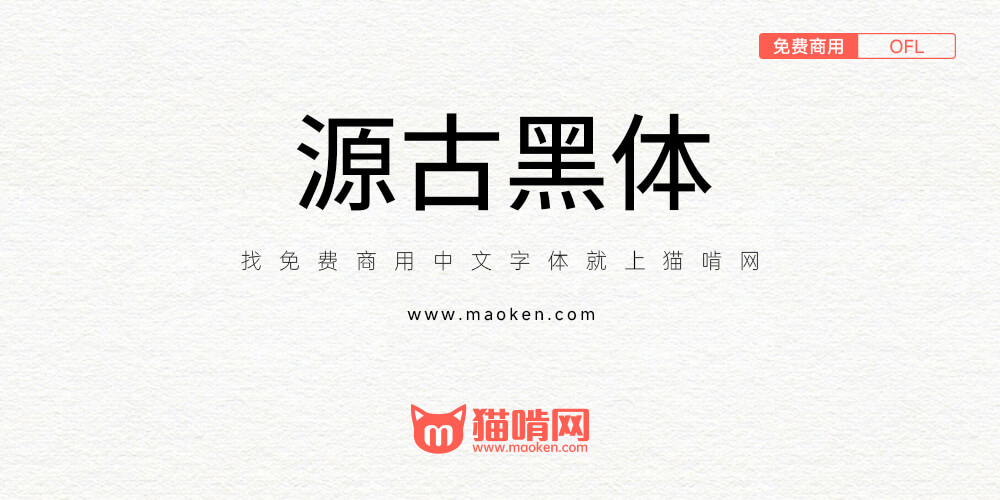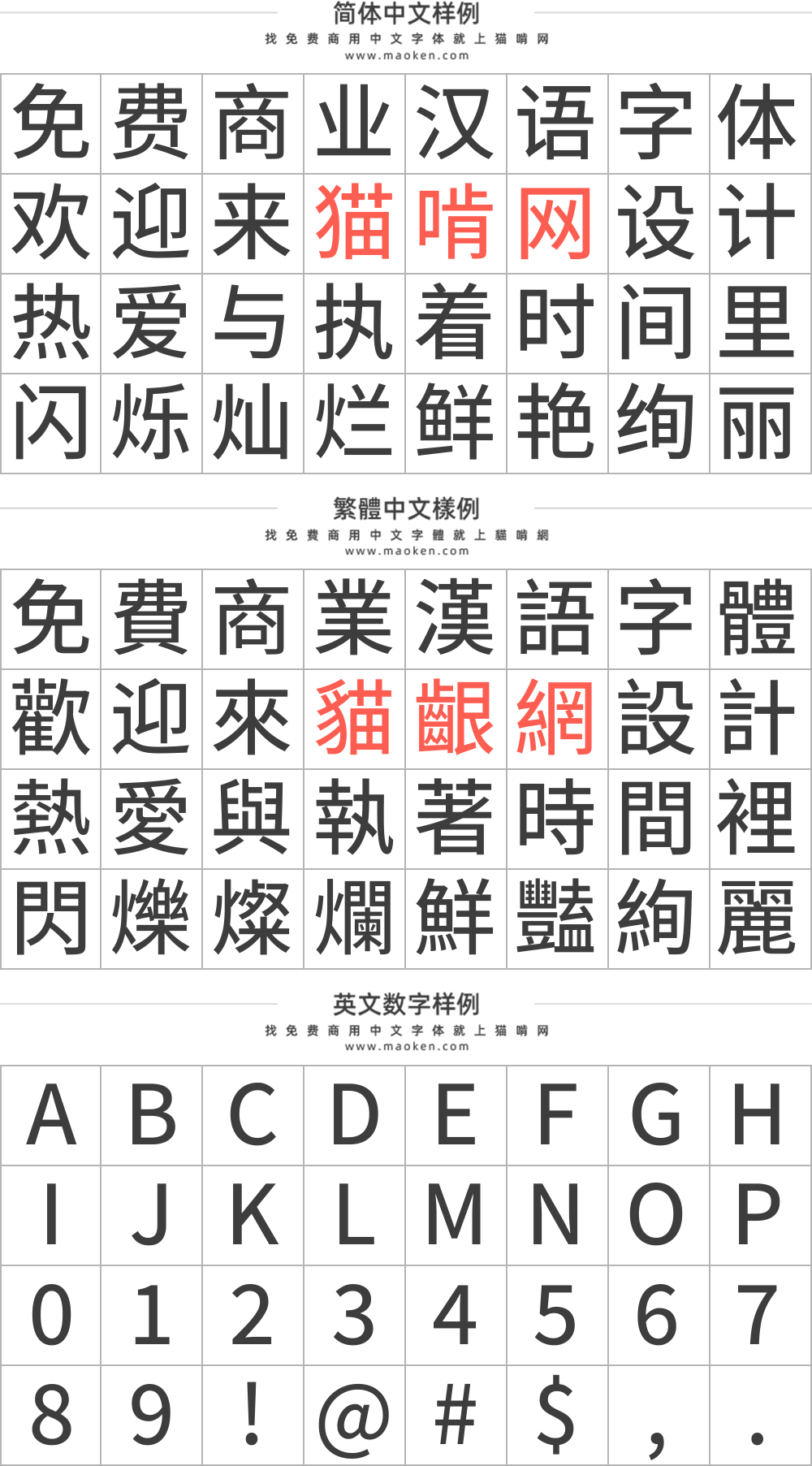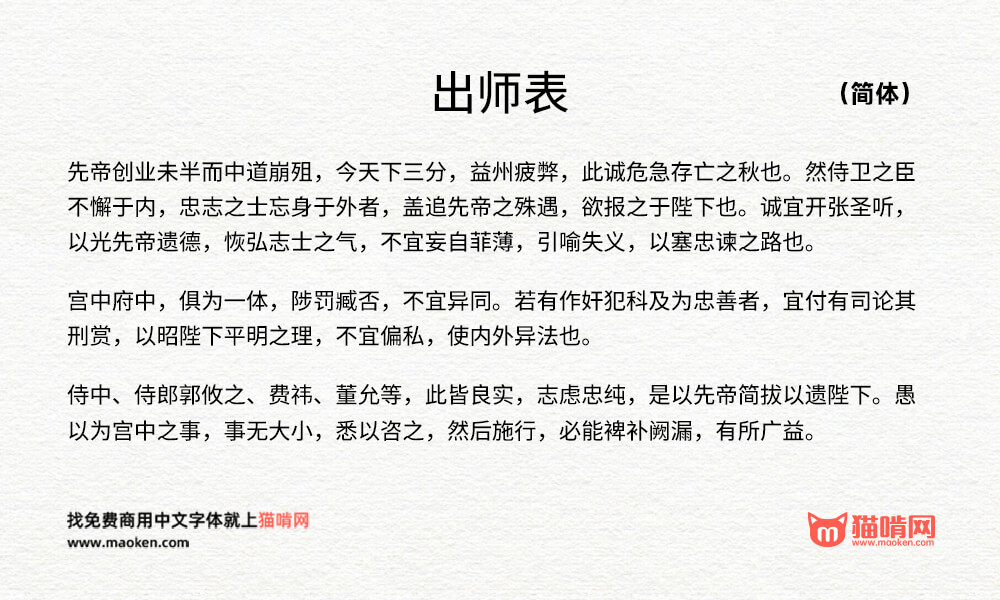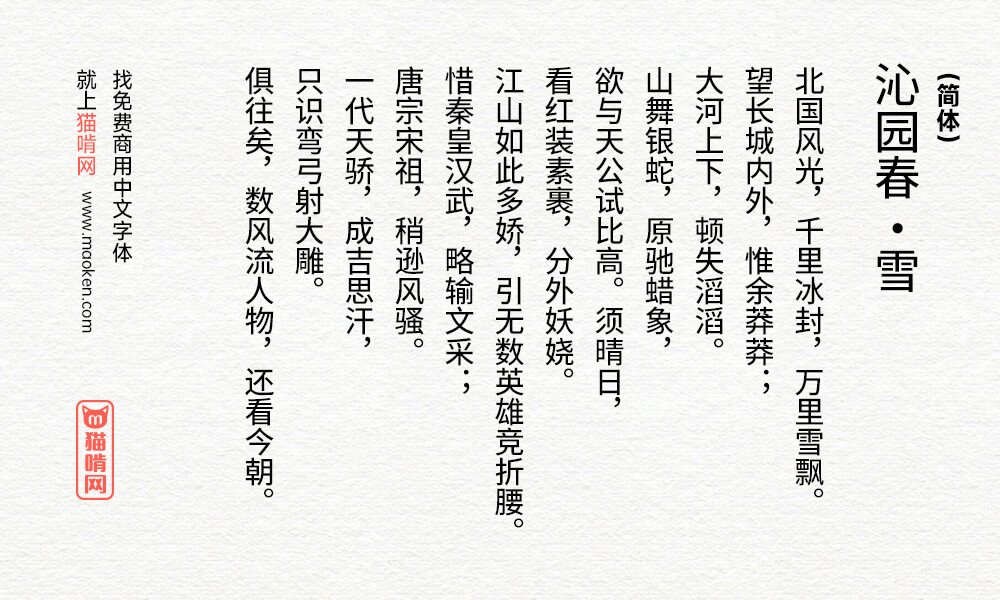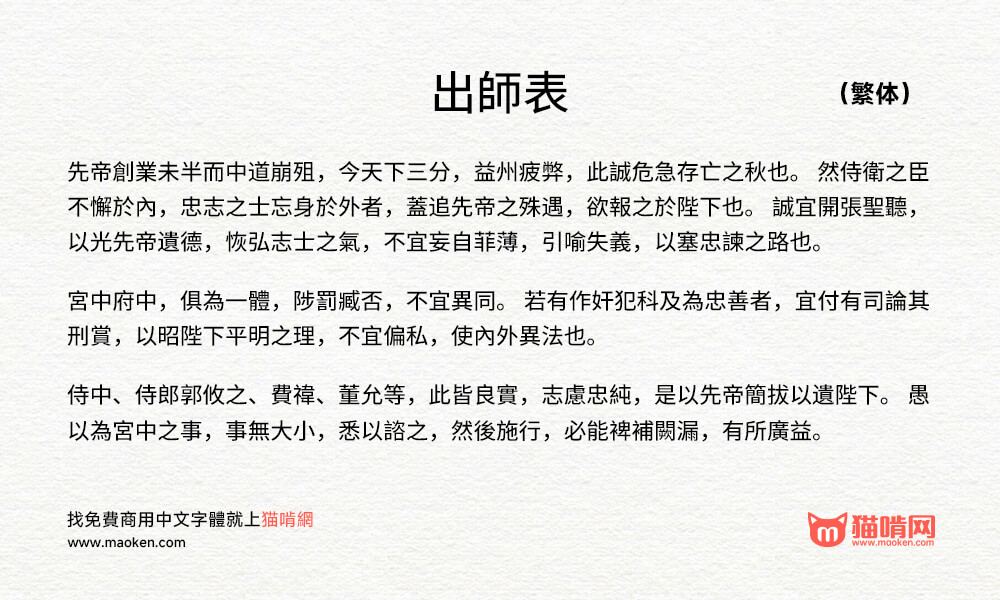
汇文系列字体的作者特里王在前段时间发布了《真·國標繁體-古籍規範字形工具包》,旨在解决《古籍印刷通用字规范》颁布后的实践断层问题。在工具包做出发布了两款古籍规范的字体源古黑体与源古宋体,黑体基于思源黑体改造,扩B区的字取自遍黑体。宋体基于思源宋体改造,扩B区的字取自文津宋体。
得益于思源丰富的地区字形,拆拆凑凑很方便就可以改出一个古籍表版本。而关于那些部件不统一的字,我有选择性地擅自进行了统一。
然后黑体和宋体各提供了两个版本,一个是仅包含古籍表表内字的纯古籍表版,一个是把古籍表外的——思源本来有的那些字一股脑放进去的“F”版本(当然这些表外字就没有按古籍表规范修改,保持思源原样)。
各位可以按需选用。日常看书写东西可以用F版,确保不缺字。
如果要作为做字体的参考或者炼丹的底子,就可以用纯古籍表版,以免被表外字误导。没错,其实这次弄这俩字体,本来就是作为炼丹工具性质的
除了这俩思源改,我的竹音仿宋和东乡明朝还在缓慢制作中,都是优先基于古籍表的构型规范做的。单独的京华老宋体古籍表版本正在调试中,后续会择日放出(坑+1)
这么多黑体,这个黑体有什么特别之处?
• 特别之处在于它是按照《古籍印刷通用字规范字形表》调整了字形写法,与一般的国标字形相比有一定的不同之处;此外增补了一些古籍所用的字。
剩下的字保留思源原来的写法我不是很认可()
• 时间精力有限吧。剩下的字还有将近一倍呢,暂时可以不急